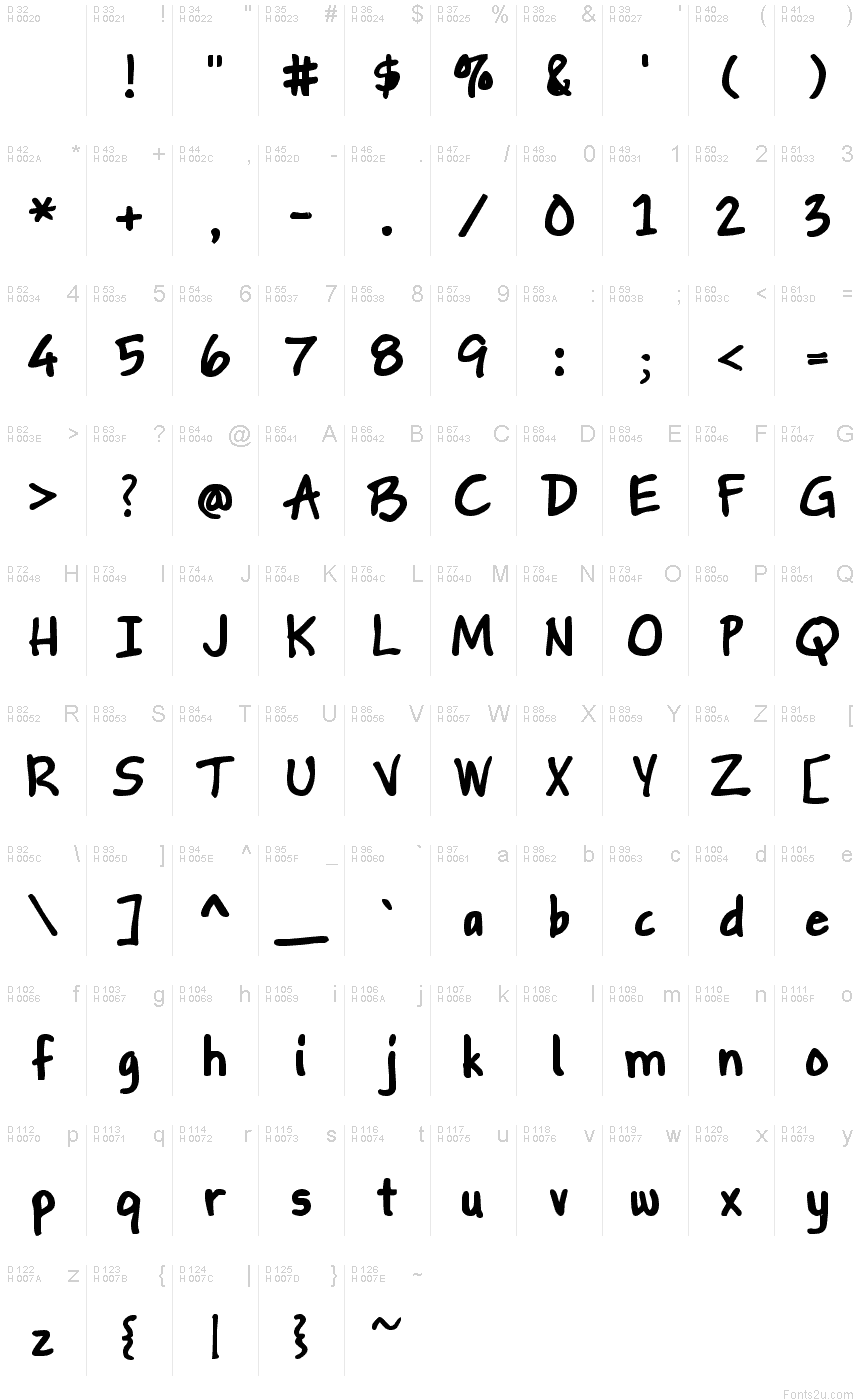
Gapstown AH Bold von Fontgrube Ah ist eine kostenlose, handschriftliche Schriftart mit einem kräftigen, markerartigen Strich, der aussieht, als wäre er flüchtig auf ein Whiteboard geschrieben worden. Die Buchstaben sind abgerundet, schwungvoll und leicht unregelmäßig, was dem Text einen lockeren, freundlichen Rhythmus verleiht, der auch in kleineren Größen gut lesbar bleibt. Der fette Schriftschnitt sorgt für eine warme, kräftige Präsenz, sodass Ihre Wörter selbstbewusst wirken, ohne ihren ungezwungenen Charme zu verlieren.
Mit Gapstown AH Bold verleihen Sie Arbeitsblättern, Kinderbüchern, Klassenzimmer-Postern, Comics, Social-Media-Grafiken und verspielten Produktverpackungen eine handgezeichnete, zugängliche Note. Diese kostenlose Schriftart glänzt besonders in größeren Überschriften. Kombinieren Sie sie für den Fließtext mit einer klaren serifenlosen Schrift, um das Layout übersichtlich und lesbar zu halten.
This is a hand printing font for those who do not need or want the artificial evenness of Comic Sans, Tekton or the like. Gapstown contains a full ISO 8859-1 character set, you can write most western European languages with it. 193 manually edited kerning pairs add to the quality of this font.